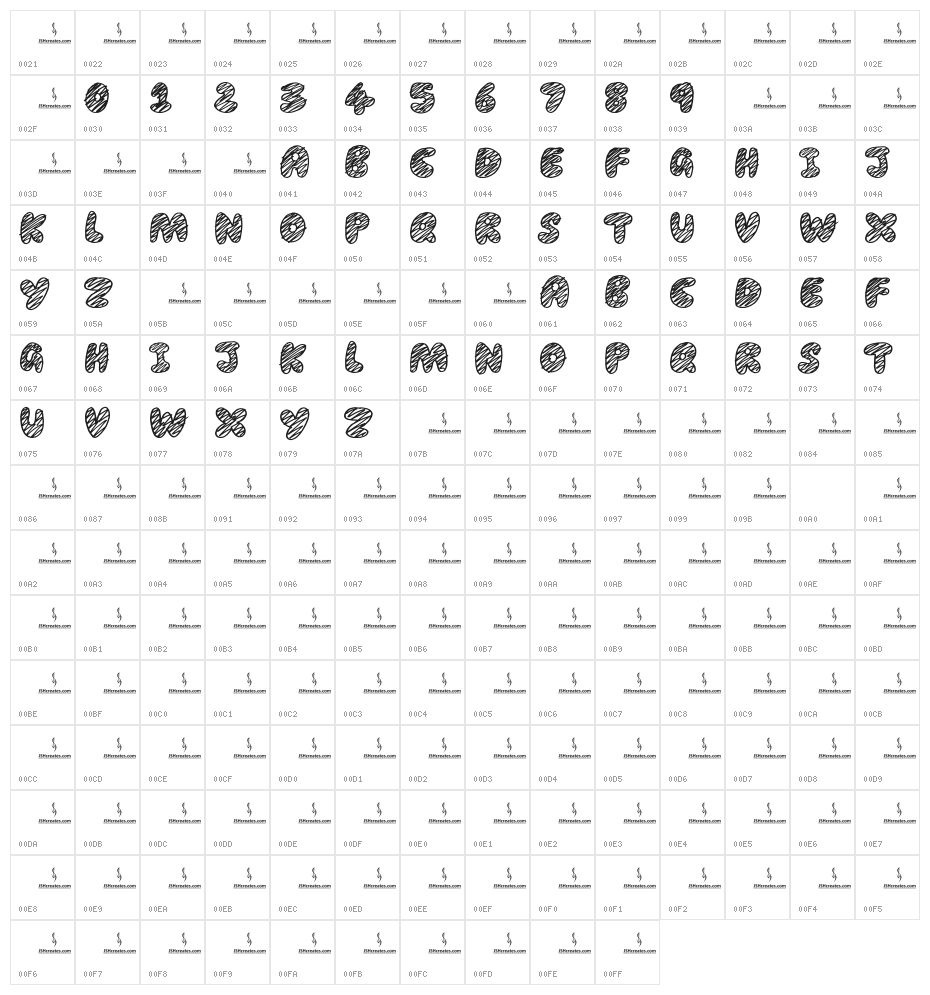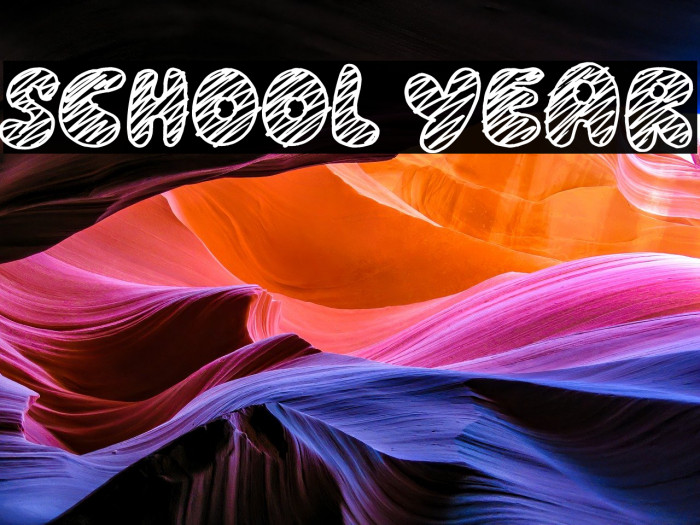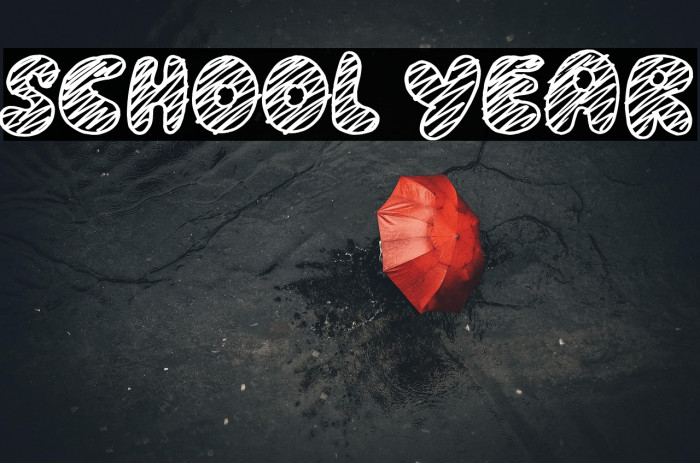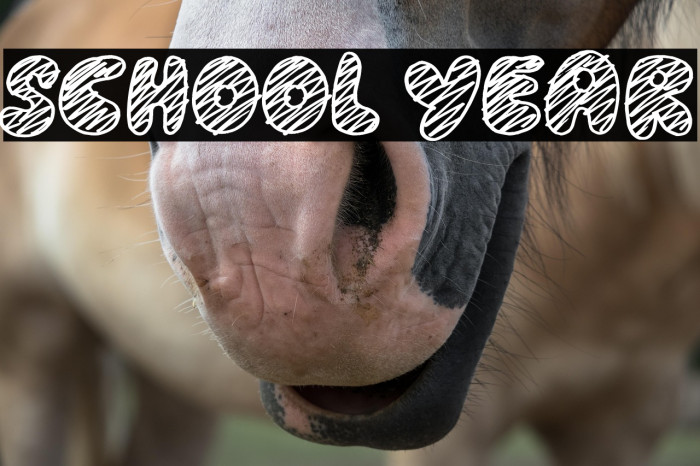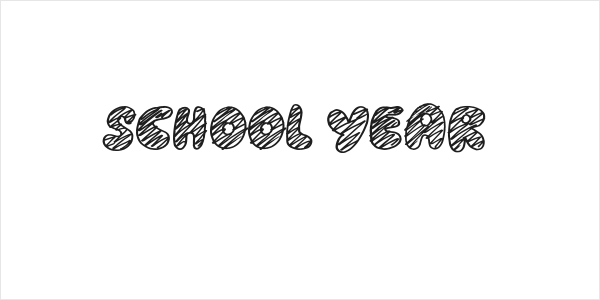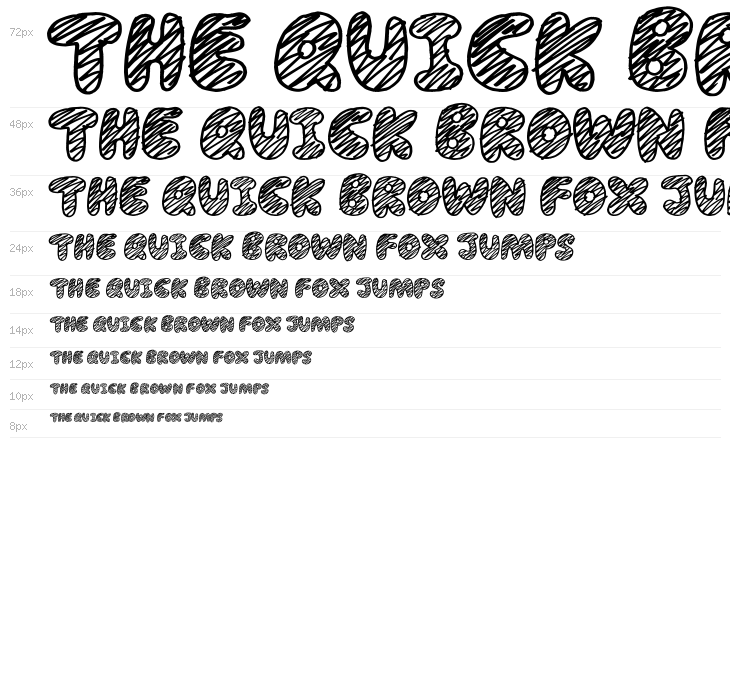
School Year Font
| Categorie | Cartoon |
| Stile generale | Playful, Casual |
| Caso d'uso | Headlines, Posters, Creative Branding |
| Progetti proposti | Ideal for children's book covers, playful posters, school projects, and creative branding. |